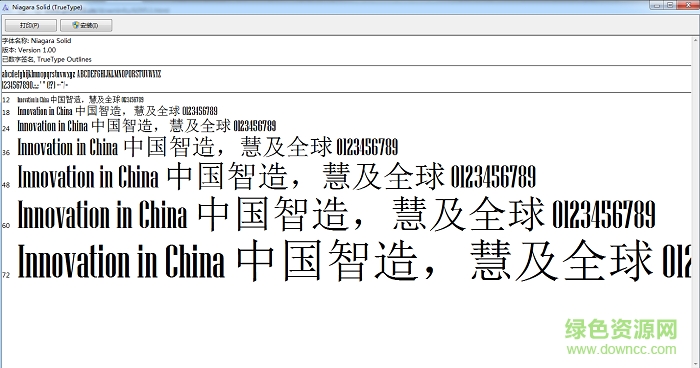
niagarasolid reg
niagarasolid reg字體是一款非?;ㄉ诘挠⑽淖煮w,該字體粗細對比明顯,挺拔好看,比較引人注目,用在一些藝術(shù)設(shè)計、創(chuàng)意海報、平面設(shè)計方面是可以的,喜歡的朋友快來綠色資源網(wǎng)下載吧!
niagarasolid reg字體特點